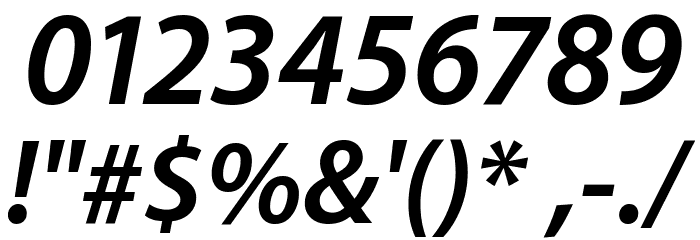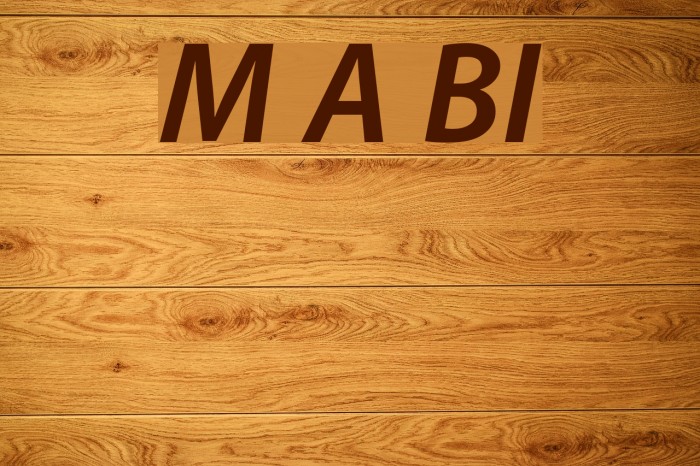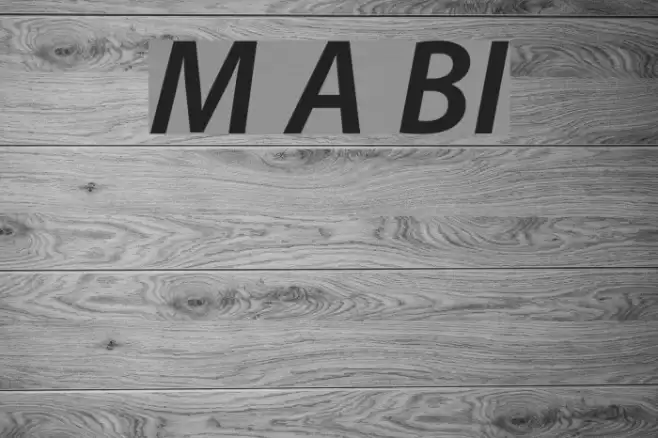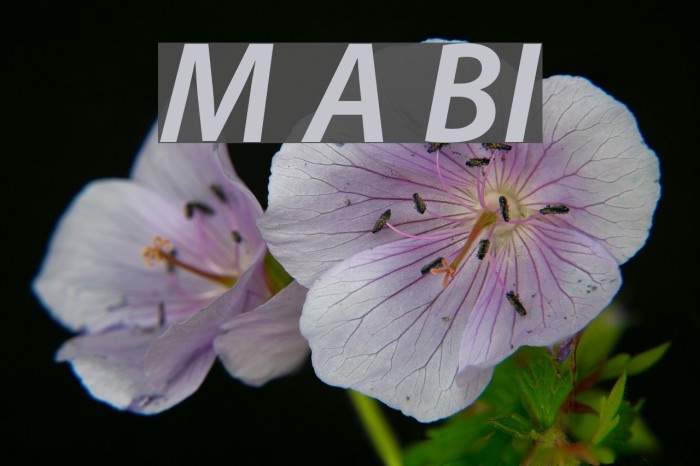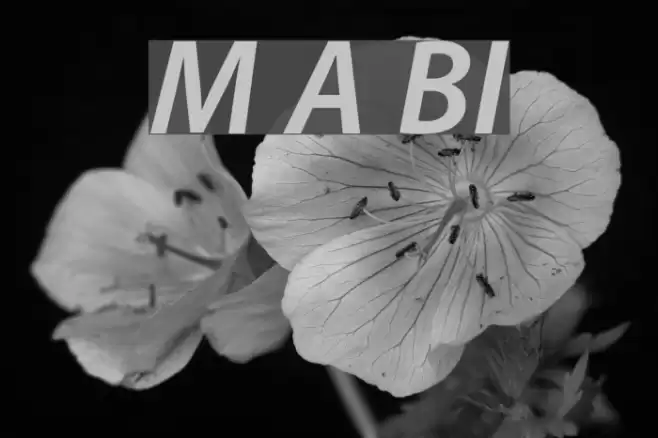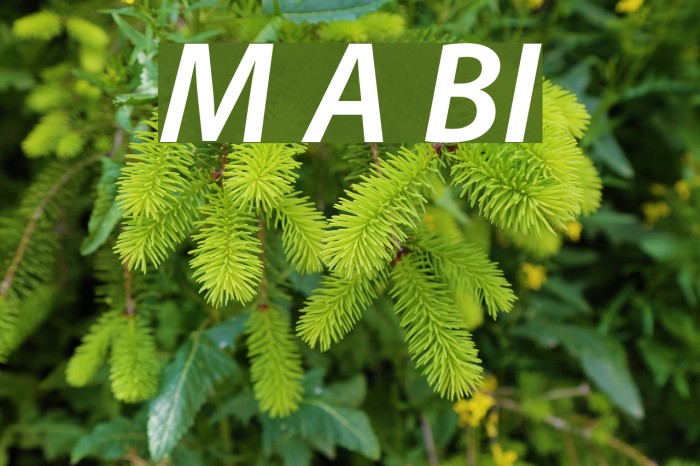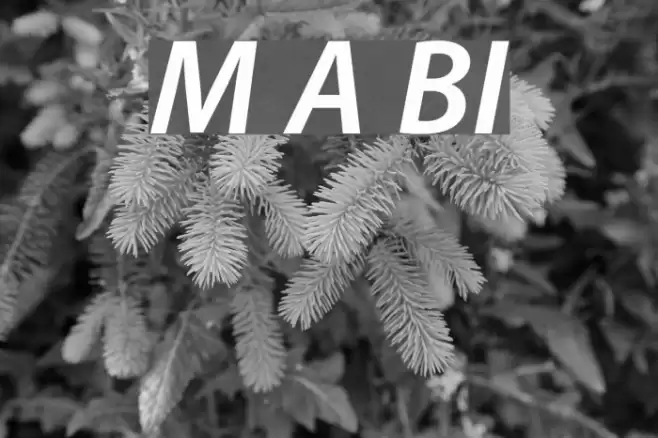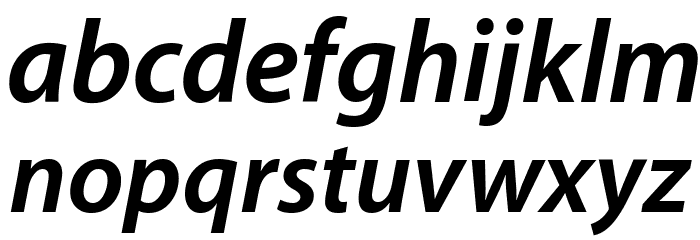
Myriad Apple BoldItalic Font
| 用途 | Headlines, Logos, Digital Media |
| おすすめプロジェクト | Ideal for branding, advertising, and digital media projects where a modern and bold statement is needed. |